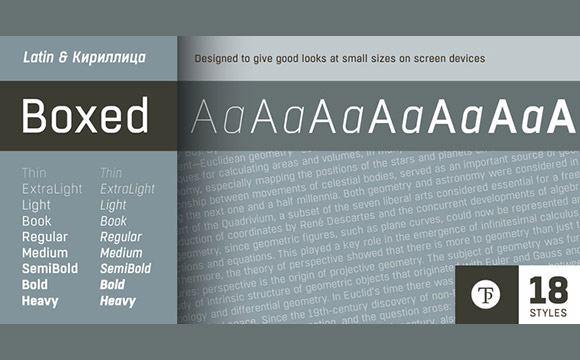
Recién salida del horno te presentamos la nueva joya tipográfica creada por nuestro maestro de las letras e insigne «Tipo Duro» Josep Patau. La nueva «criatura» se llama Boxed por su marcada anatomía geométrico-modular que le permite adaptarse a la rejilla de pixeles de un monitor para ofrecer una apariencia nítida y un fluido ritmo de lectura.
Es una extensa tipografía de 18 pesos, pensada y diseñada para lucir bien en dispositivos de pantalla en tamaños pequeños, aunque no renuncia a ofrecer una buena apariencia sobre papel. Gracias a su extenso rango de pesos, es fácil compensar la mancha de los caracteres entre los diferentes estilos CSS. Dispone de un extenso juego de caracteres latinos e incluso los del cirílico.